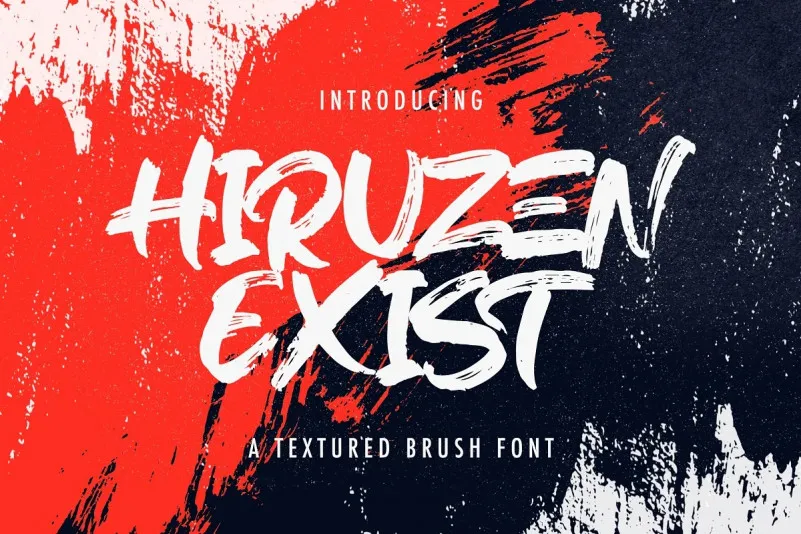
Esta fonte ‘Hiruzen Exists’ é uma criação única do designer StringLabs que oferece uma sensação de desafio e originalidade ao seu design. Com seu traço rústico e brusco, ela se destaca como um texto embaciado perfeito para quem busca algo diferenciado em suas criações digitais. Se você está procurando por algo mais que a mera regra básica do tipo, essa fonte é uma escolha ótima. Ela traz consigo um toque de criatividade e beleza única, tornando-a uma adição incrível para qualquer design personalizado ou web-site. Não deixe de explorar sua versão completa para adicionar um toque inovador a seu próximo projeto gráfico.